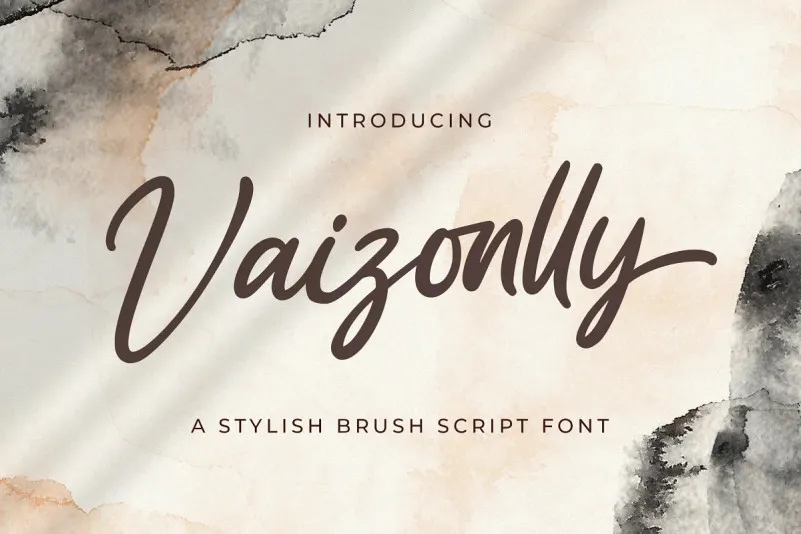
Vaizonlly Script Font – Fonte Grátis
Vaizonlly Script Font
A Vaizonlly Script Font é uma embalagem única de tipo feito à mão que se destaca por sua elegância natural e estilo inconfundível. Cada letra da Vaizonlly tem um toque autêntico, criado através do uso de técnicas de escrita a mão, proporcionando um toque nostálgico e único às suas criações gráficas. A StringLabs trouxe à vida esta fonte especializada no estilo Script, oferecendo designers e aficionados por design uma ferramenta poderosa para introduzir um ar autêntico em qualquer projeto. Sua tipografia tem o toque perfeito de casualidade que torna a Vaizonlly Script Font uma escolha irresistível para quem deseja adicionar um toque pessoal às suas ideias de design, seja para criações publicitárias ou sites. Com a Vaizonlly Script Font, você pode criar designs impressionantes e inesquecíveis.